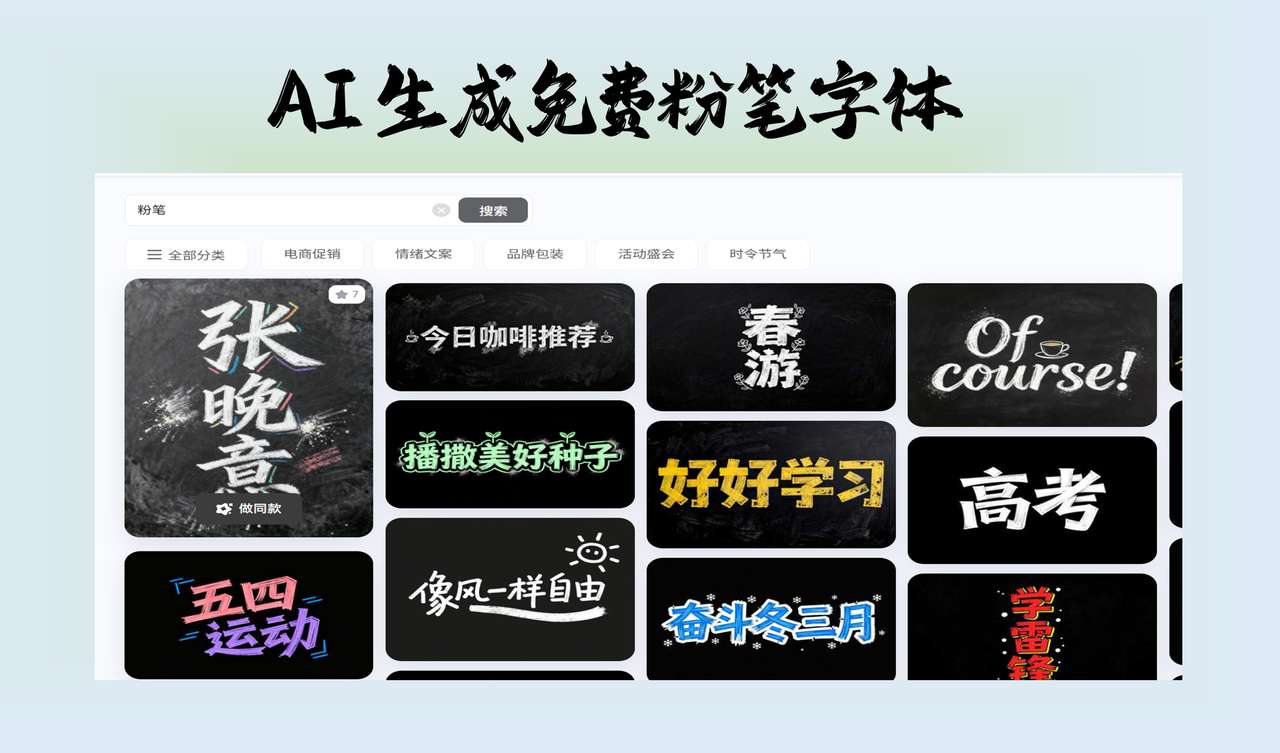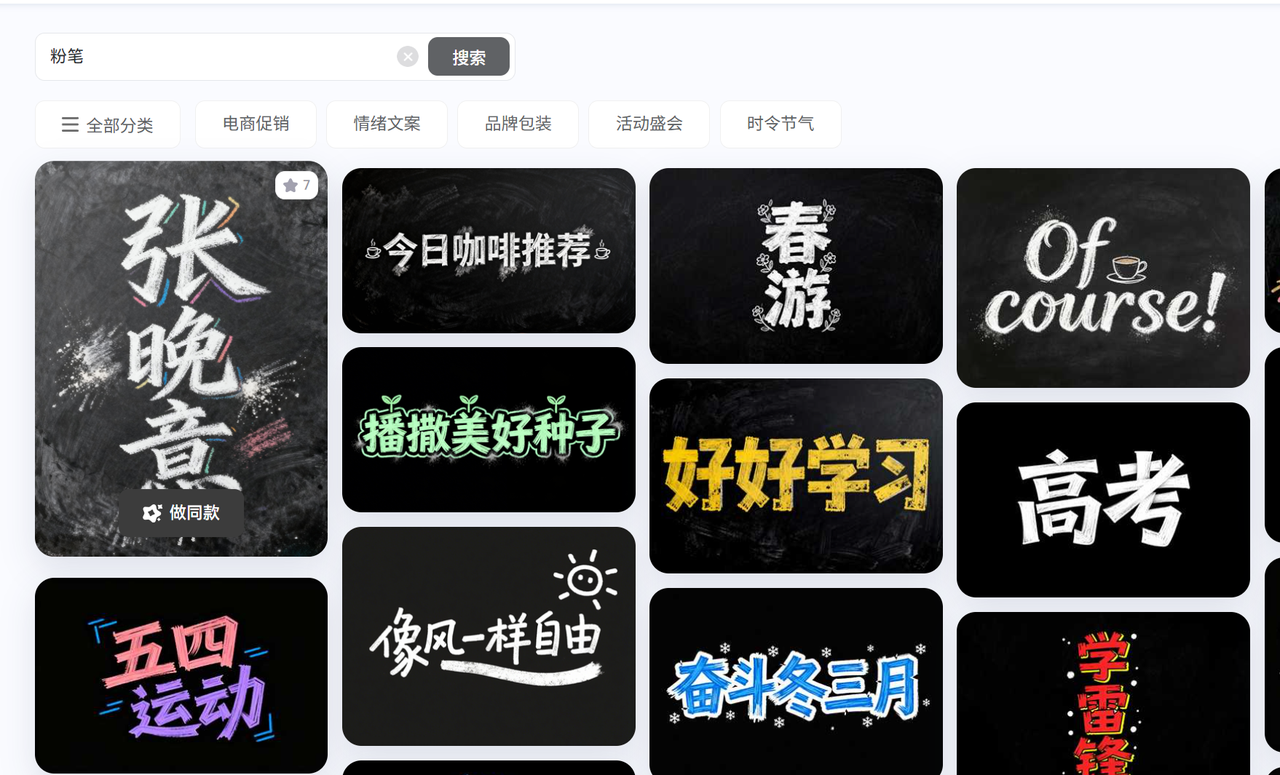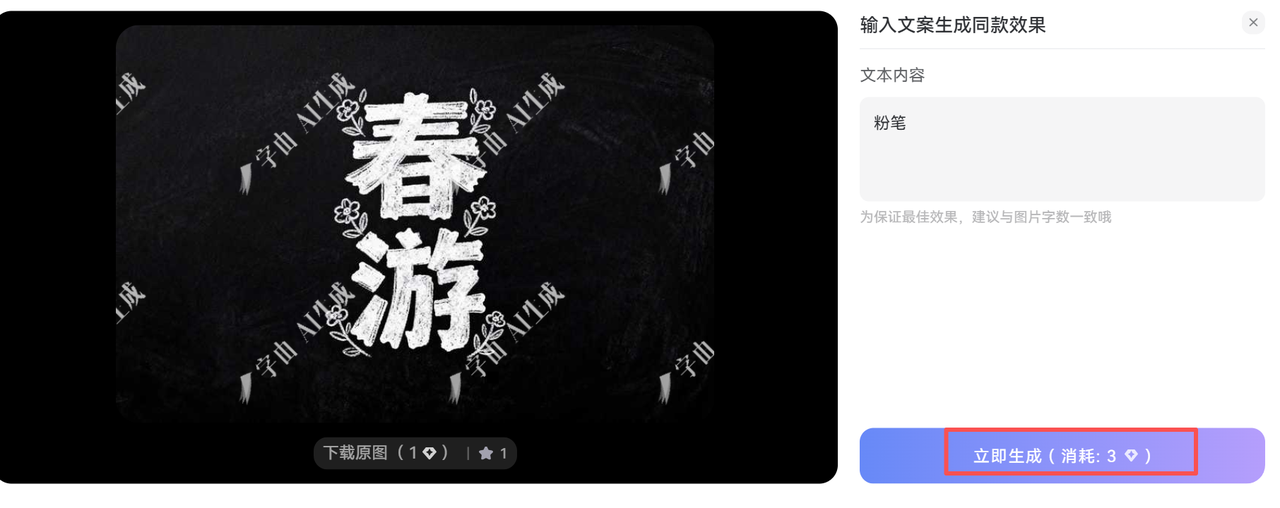
如何免费下载粉笔字体?教你用AI直接生成
做设计这几年,我遇到过不少让人头疼的场景:客户要求做黑板报风格的海报,老板让设计一套教育类的宣传物料,或者策划活动需要复古手写感的视觉效果。每次碰到这种需求,我第一反应就是去找粉笔字体。
本文就给大家介绍今年我发现的一款粉笔字体生成工具,生成后可以免费下载使用
AI 字体生成功能介绍
字由除了提供现成的字体下载和字体管理功能,还上线了一个特别实用的工具——字体设计AI生成器
这个工具我用过几次,体验确实不错。简单来说,它能通过AI技术生成各种风格的字体效果,粉笔字体就是其中一种。你只需要输入想要的文字内容,选择"粉笔风格"或相关的预设模板,系统就会自动生成带有粉笔质感的字体效果。
比如你手头正在赶一个项目,需要快速出几个粉笔字效果的标题或标语,但又不想花时间去安装、测试各种字体。这时候直接用 AI 生成器,几秒钟就能拿到可用的素材,效率很高。
生成的字体效果可以直接下载为图片格式使用,也可以作为设计参考,对我来说,这是一个很好的设计辅助工具,节省了不少时间。
页面提供模板搜索功能,可以直接搜索"字体粉笔",就能查看丰富的字体模板
选择一个粉笔字体模板生成
选择一个喜欢的粉笔字体模板,输入自己的文案,点击生成即可。
生成后的效果
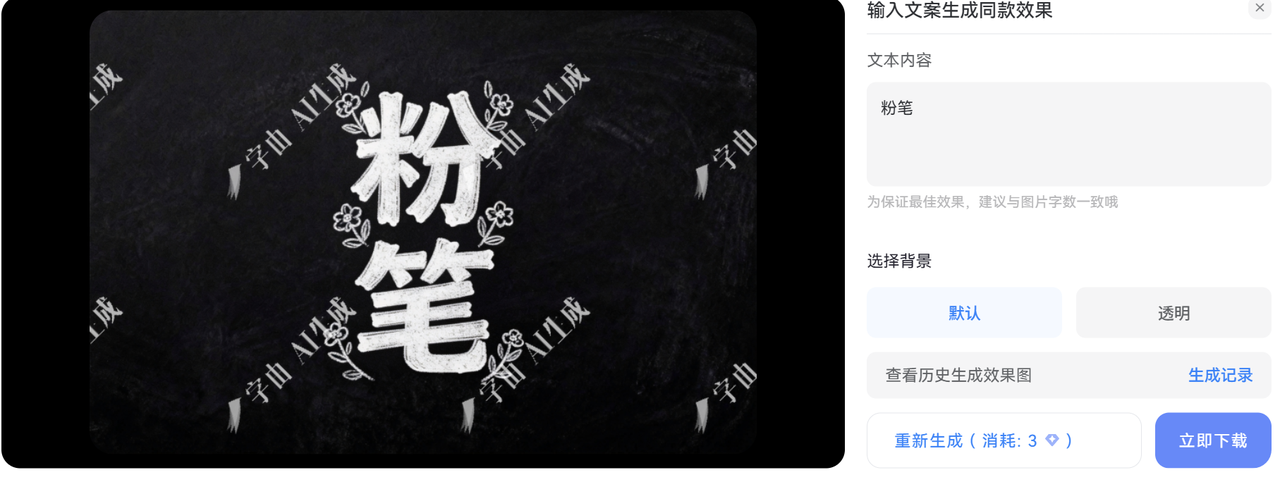
我常用的几款粉笔字体模版
像风一样自由
非常轻松愉快的一个粉笔字体,适合旅行、慢生活的设计作品
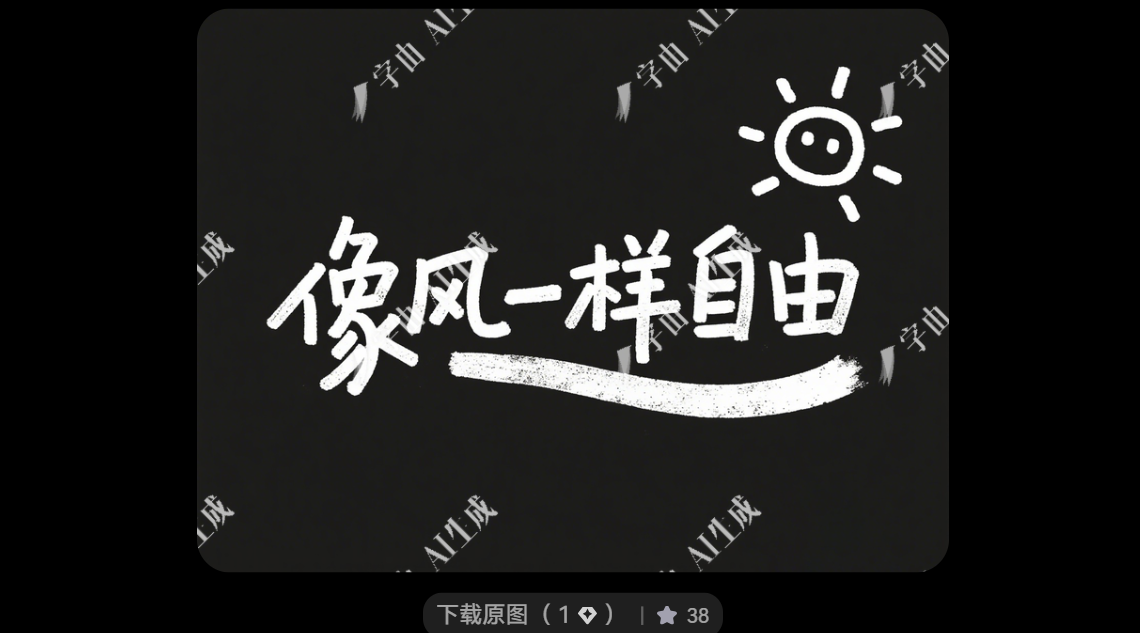
今日咖啡推荐
相信大家都看到过类似的字体,非常适合小众有格调的美食领域
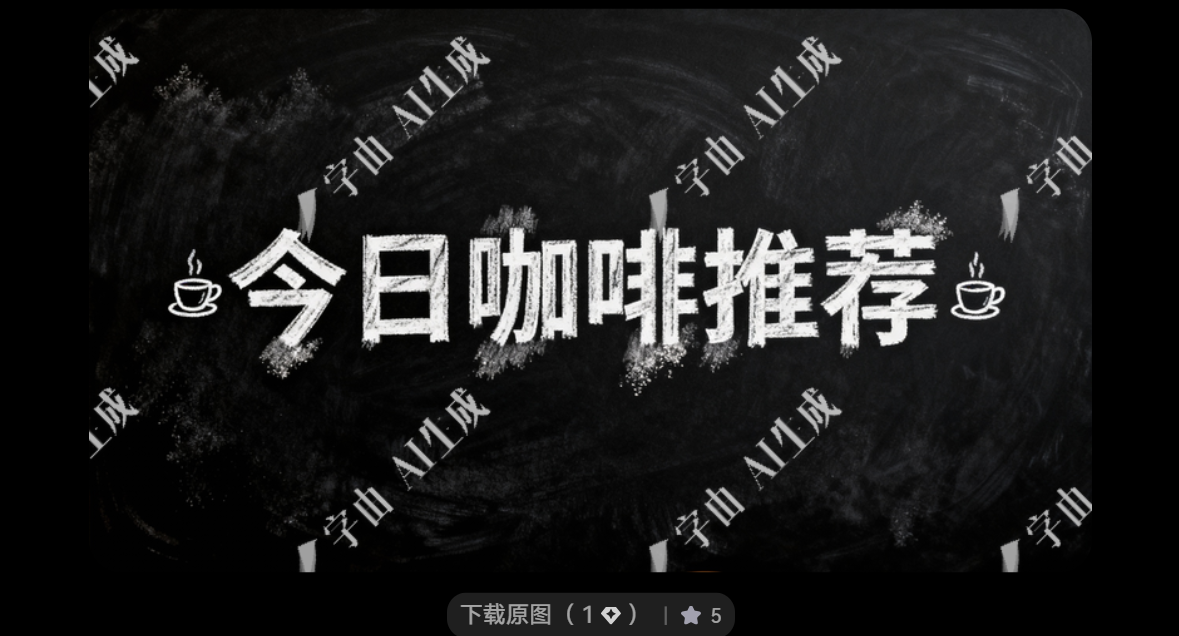
免费商用的粉笔字体下载,对我来说已经不是一个难题了。通过字由AI生成工具,基本覆盖了我日常工作中的大部分需求。不用再到处找资源,不用担心版权问题,设计效率提升了不少。如果你也经常需要用到粉笔风格的字体,建议试试字由AI生成字体工具。